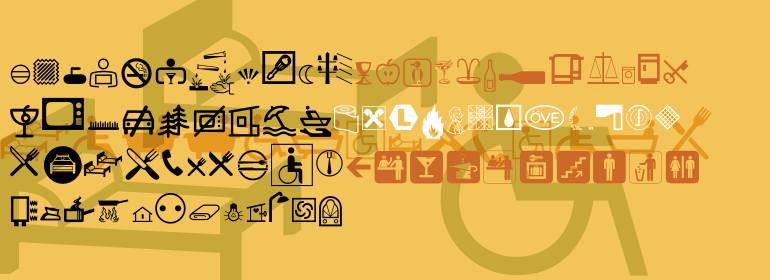
Communications
Communications,这款字体结构工整、笔画清晰,兼顾美观与易读性,适用于标题、正文、海报、包装、LOGO 等多种场景。字形优雅稳定,风格百搭耐看,适配日常排版与创意设计,让文字呈现更舒适、更具质感。Communications一笔一画,皆是细节,以均衡的比例、流畅的线条打造舒适视觉体验,字形端正大气,风格简约现代。无论是商业设计、品牌宣传还是日常排版,都能轻松驾驭,让文字更有格调与力量。Communications字体下载。